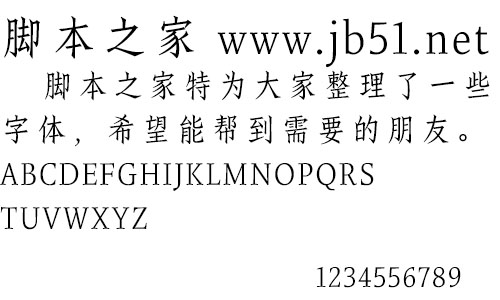
方正國(guó)美進(jìn)道體由中國(guó)美術(shù)學(xué)院漢字設(shè)計(jì)創(chuàng)新研究所出品的藝術(shù)字體,該字在保證應(yīng)用場(chǎng)景中可辨性和適讀性的同時(shí),強(qiáng)調(diào)版刻、書(shū)法、印刷在同一款字體中的平衡與共存,適合應(yīng)用于藝術(shù)設(shè)計(jì)、平面宣傳設(shè)計(jì)、網(wǎng)頁(yè)設(shè)計(jì),書(shū)法等領(lǐng)域。
作為國(guó)內(nèi)首款高校定制字體,方正國(guó)美進(jìn)道體在保證應(yīng)用場(chǎng)景中可辨性和適讀性的同時(shí),強(qiáng)調(diào)版刻、書(shū)法、印刷在同一款字體中的平衡與共存,力求打破字庫(kù)中常見(jiàn)規(guī)格化、工業(yè)化、模式化的視覺(jué)形態(tài),在傳承中國(guó)美術(shù)學(xué)院文脈的同時(shí),傳遞國(guó)美的溫度。。